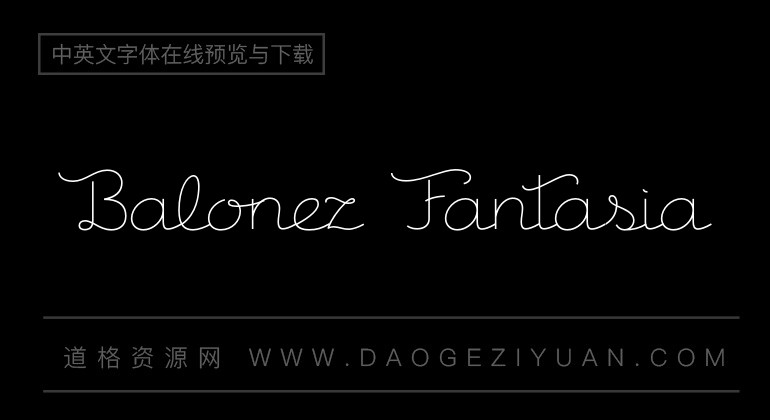
Balonez Fantasia 是一种华丽的手写字体,适用于许多不同类型的设计项目。这种字体的特点是由自然的笔画和精美的弧线组成的,为文字赋予了一种流畅、优美的感觉。 Balonez Fantasia 字体包括大写字母、小写字母、数字和一些标点符号。它的设计风格适用于许多类型的设计项目,例如宣传册、海报、包装、广告、时尚和艺术类设计等。这种字体的使用可以使设计看起来更加华丽、精致和有品味。 Balonez Fantasia 字体的主要特点包括: - 华丽的手写风格 - 流畅、优美的笔画和曲线 - 可适用于各种类型的设计项目 - 包括大写字母、小写字母、数字和标点符号 如果你正在寻找一种华丽的手写字体,可以考虑使用 Balonez Fantasia。内容介绍
Balonez Fantasia是一款非常不错的手写艺术字体,具有很好的视觉感,适合于文化类的宣传设计、商业类品牌的广告和产品包装设计以及个性化文字排版等较多场景。